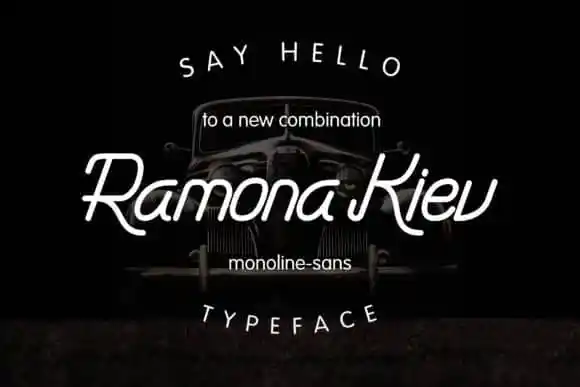
Ramona Kiev – Monoline Font – Download Grátis
Ramona Kiev Monoline é uma fonte sans-serif monolínea introduzida por 0001themes que traz consigo a elegância vintage e a sofisticação moderna em um só design. Inspirada no estilo de impressão de letrapress do velho mundo, esta fonte combina formas curvadas de serif com linhas retas característicos da sans-serif, resultando em uma combinação única que transmite uma atmosfera vintage contemporânea. Com seu aspecto moderno e elegante, é perfeito para criar cartões de convidados encantadores, arte de papelaria sofisticada e postagens sociais chamativas, assim como cartas de agradecimento criativas. Este projeto foi originalmente concebido e compartilhado por candacreative. A fonte carenciada tem um toque refinado de elegância que combina elementos autênticos de escrita à mão com o encanto da serif. Ramona Kiev Monoline é uma opção perfeita para designers buscando criar materiais de gráfica que combinam sofisticação e nostalgia, seja em cartões de aniversário adoráveis até postagens sociais chamativas.